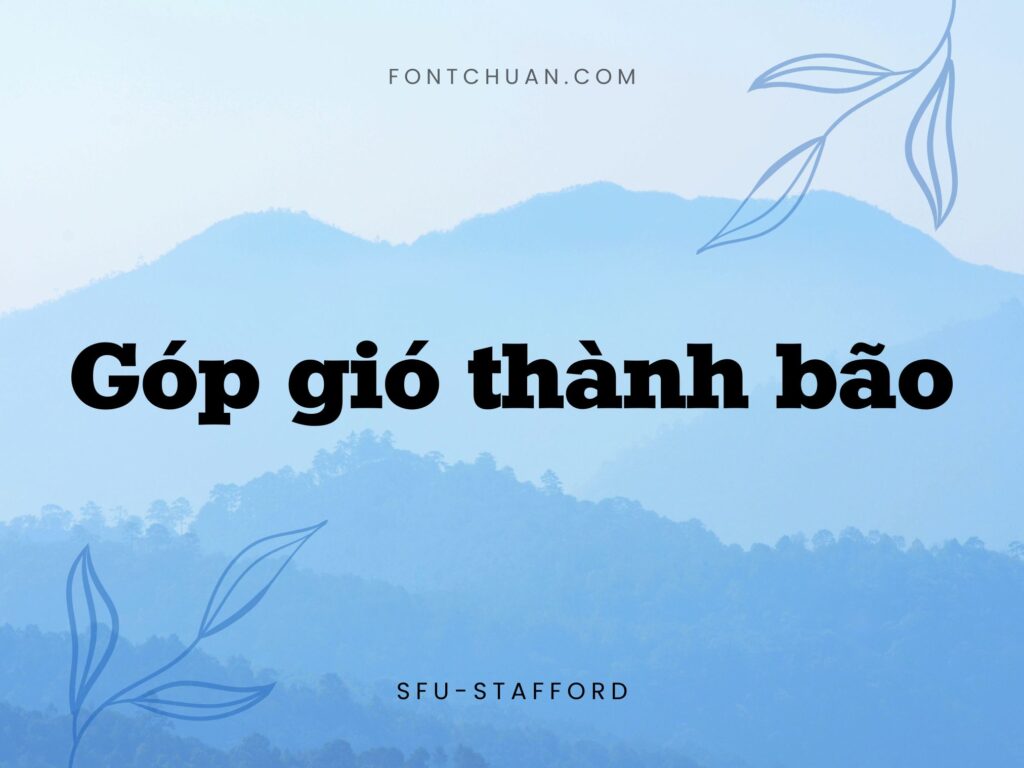
Font SFU Stafford Việt Hóa
Font SFU Stafford Bold là một kiểu chữ serif đậm nét, mang phong cách cổ điển và trang nhã. Với các đường nét mạnh mẽ và cân đối, font này tạo cảm giác chuyên nghiệp và dễ đọc, phù hợp cho nhiều mục đích sử dụng khác nhau.
SFU Stafford Bold lý tưởng cho các dự án thiết kế logo, tiêu đề, bao bì sản phẩm và các ấn phẩm quảng cáo. Các ngành nghề như quảng cáo, giáo dục và công nghệ có thể tận dụng font này để tạo điểm nhấn trong thiết kế. Ngoài ra, font cũng thích hợp cho các sự kiện như Tết, Giáng sinh, Valentine và các lễ hội khác.